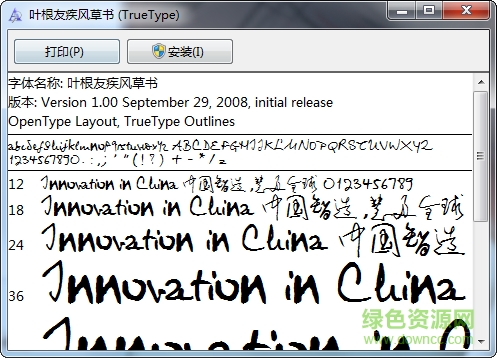
軟件介紹 軟件標簽: 葉根友疾風草書 葉根友 草書 葉根友疾風草書字體是一款非常經典的草書字體,葉根友系列字體可以說是設計師門的必備字體了,這款草書字筆鋒雄厚,剛勁有力,喜歡的就來下載吧。安裝使用方法:方法一:控制面板/字體/文件/安裝新字體;方法二:直接將字體復制到C:\WINDOWS\Fonts 軟件截圖 上一張下一張(1 / 1) 安裝詳細截圖 猜你喜歡 古風字體 草書字體 古風字體 古風字體,顧名思義,就是有古代風韻的字體。這類字體一般給人的感覺,都是比較飄逸的,非常好看,很有意境,如:南構唐寶楷字體、文悅古典明朝字體、葉根友古刻體字體等,喜歡的朋友,趕快下載體驗吧! 查看更多>> 南構唐寶楷字體簡體 5.85M/中文/2.1/ttf下載 造字工房文研常規(guī)體 1.04M/中文/10.0/下載 漢儀曉波折紙體 823KB/中文/10.0/下載 白舟鯨海酔侯書體 3.16M/中文/10.0/ttf版下載 白舟隼風毛筆書法字體 4.19M/中文/10.0/下載 白舟草書教漢字體 464KB/中文/10.0/下載 草書字體 草書字體是一款設計師必備的設計字體,因其字跡潦草,風格飄逸,很多人也叫它潦草字體,草書字體在logo設計、廣告制作等方面使用的都較多,下面分享的是一些常用草書字體合集。 查看更多>> 伊筠幸運草免費字體 6.84M/中文/10.0/下載 孫過庭草體字體 1.37M/中文/10.0/ttf下載 于右任草書常規(guī)字體 9.29M/中文/10.0/下載 漢儀孫萬民草書字體 1.95M/中文/1.4/下載 衡山毛筆草書體 3.59M/中文/10.0/下載 qq漢儀長草體ttf 3.37M/中文/6.0/下載 其他版本下載 標題 大小 更新日期 下載 金梅毛草書 2.50M 2016-05-16 下載 博洋草書3500 1.25M 2016-05-16 下載 毛澤東草書字體 1.24M 2016-05-16 下載 草書字體合集 10款 20.29M 2016-05-16 下載 書法坊章草體 1.47M 2014-12-23 下載 葉根友刀鋒黑草 免費版 2.12M 2016-03-24 下載 黎凡草書繁體 3.78M 2016-07-01 下載 下載地址 電腦版 葉根友疾風草書 免費版 點擊報錯 軟件無法下載或下載后無法使用,請點擊報錯,謝謝! 關閉報錯反饋 請描述您所遇到的錯誤,我們將盡快予以修正,謝謝! *必填項,請輸入內容 本類最新 葉根友字體庫打包 共18款 葉根友風帆特色簡體 免費官方版 葉根友哲在手寫字體 官方版 南構村花手寫體ttf版 南構王小花手寫ttf常規(guī) 南構日漫風字體 用戶評論 熱門評論 最新評論 發(fā)表評論 查看所有評論(0) 昵稱: 請不要評論無意義或臟話,我們所有評論會有人工審核. 字數: 0/500 (您的評論需要經過審核才能顯示)